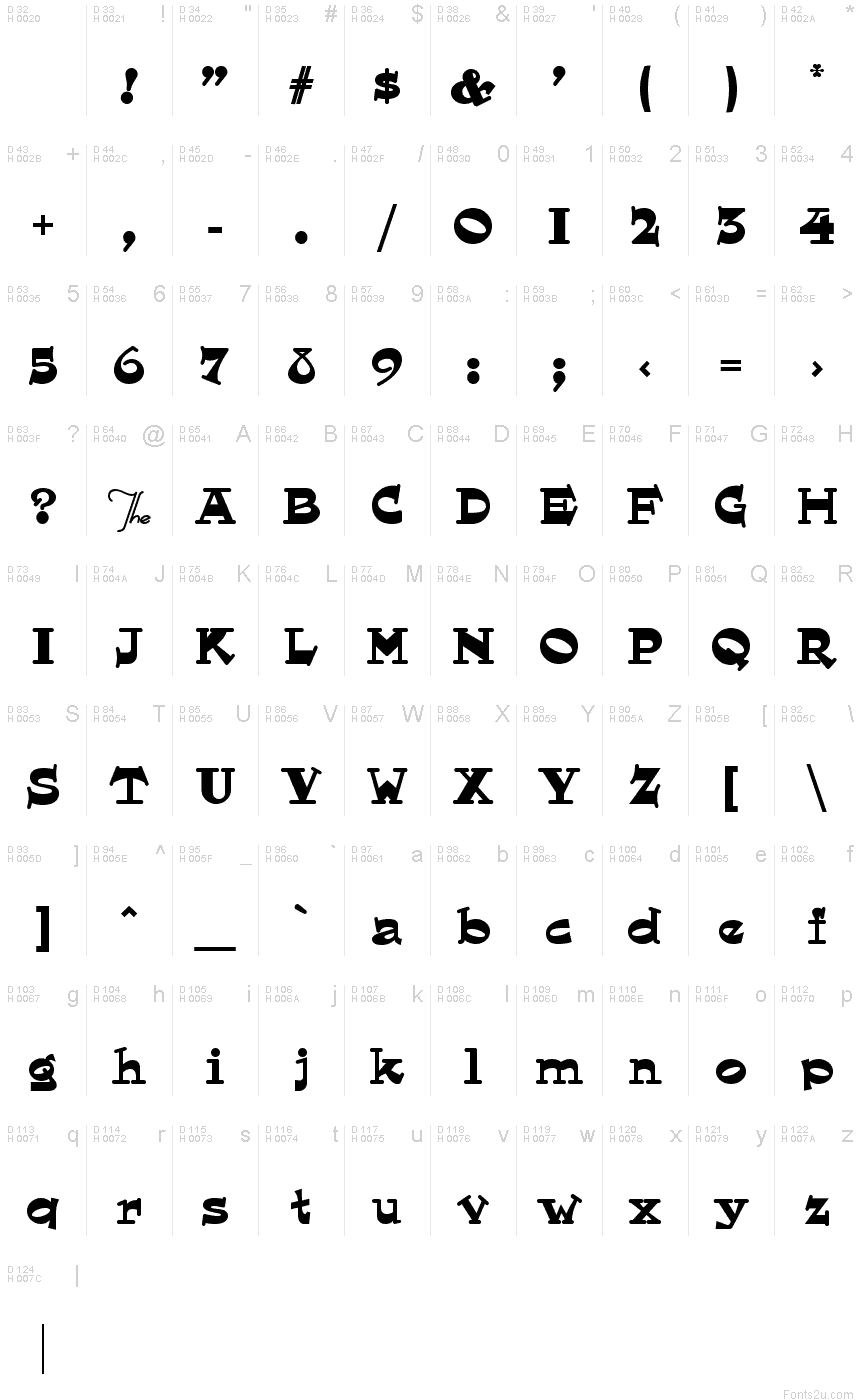
Hornswoggled
由 Nick Curtis 设计的 Hornswoggled 是一款免费的复古展示型字体,字形粗犷饱满,笔画带有俏皮的圆润感。厚实的笔画和球状的内部空间,赋予了每个文字充满活力的海报质感,仿佛是从被太阳晒褪色的老旧广告牌上摘下的马戏团字体。尽管它个性十足,但字间距依然稳重且易读,因此即使是简短的文本排版也能产生强烈的视觉冲击力,而不会显得杂乱无章。
使用 Hornswoggled,您可以为标题、活动海报、派对邀请函、书籍封面、包装设计以及独特的 Logo 概念注入一种温暖、复古的魅力,且在屏幕显示上依然生动鲜活。这款免费字体在大字号和加粗显示时最为出色;在小字号排版时,建议将其与简洁的几何无衬线字体搭配使用,以保持布局的平衡和易读性。